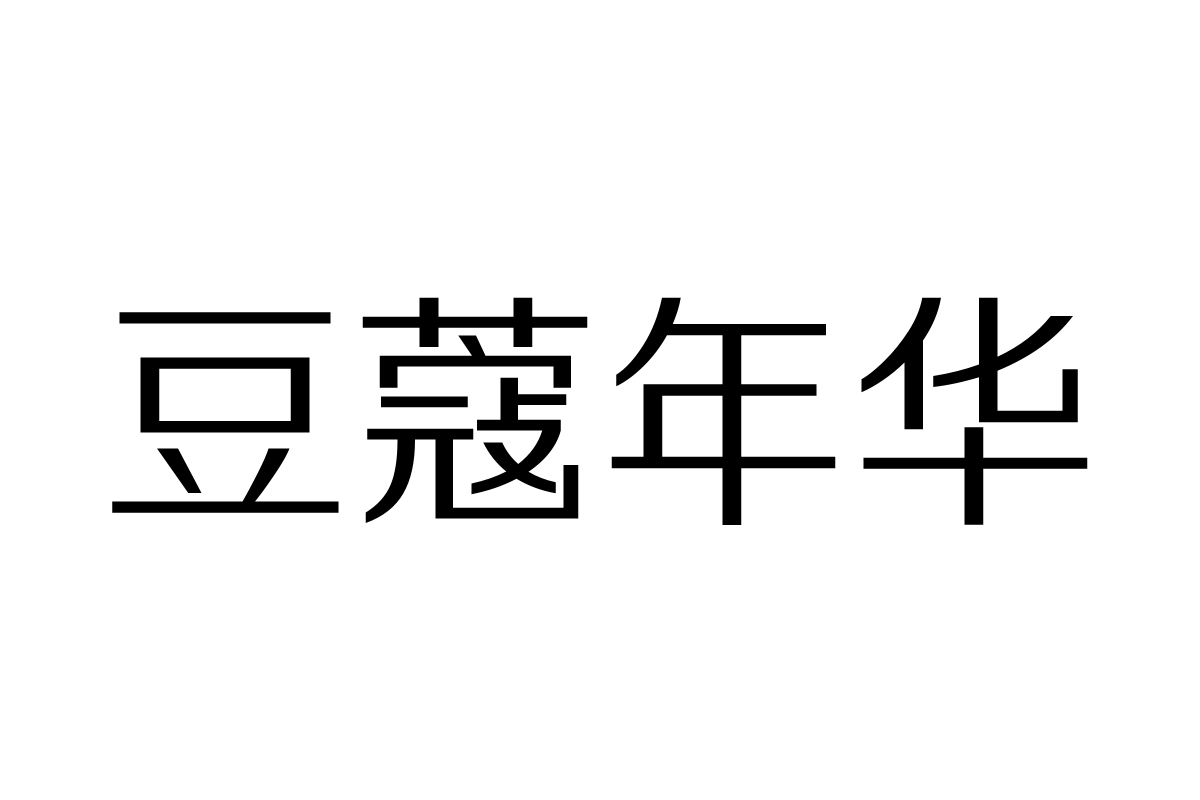
三极正黑体是一套中文字体,由方正字库公司设计并发布。它是一款具有现代感和科技感的字体,适用于各种商业、科技、教育等领域的印刷品和电子媒体。
三极正黑体的字形特点是:笔画粗细适中,结构紧凑,线条流畅,易于阅读。它的设计风格简约而不失个性,既有传统书法的韵味,又融入了现代平面设计的元素。
三极正黑体的应用场景非常广泛,包括报纸、杂志、广告、包装、书籍、网页等各类印刷品和电子媒体。它适用于需要强调品牌特色、提升设计品质的商业宣传材料,也适用于教育领域的书籍封面、教材插图等。
总的来说,三极正黑体是一款实用性强、适应性广的中文字体,能够满足不同行业、不同领域的设计需求。